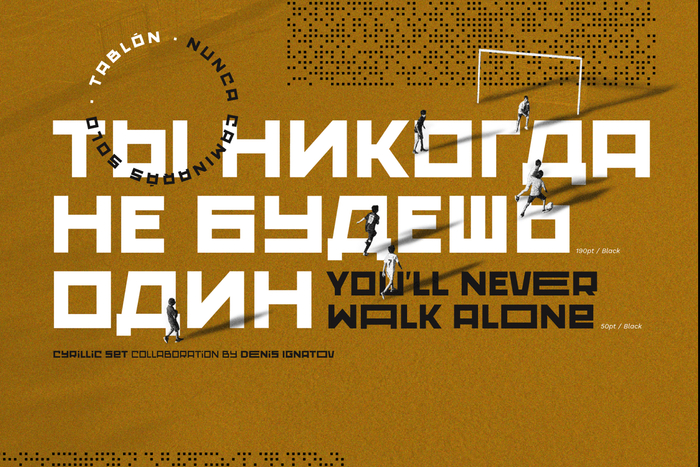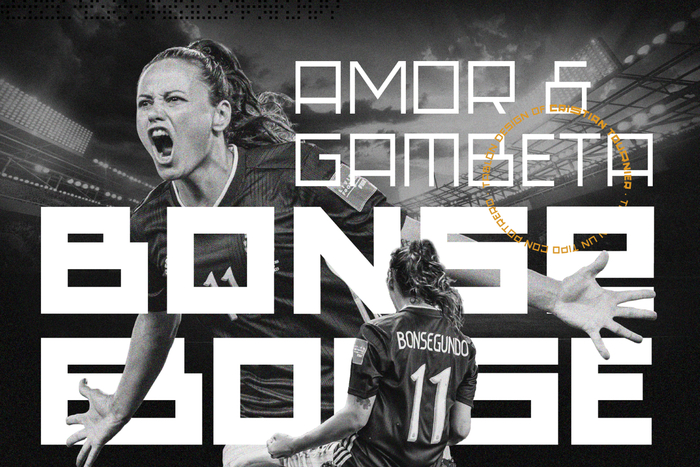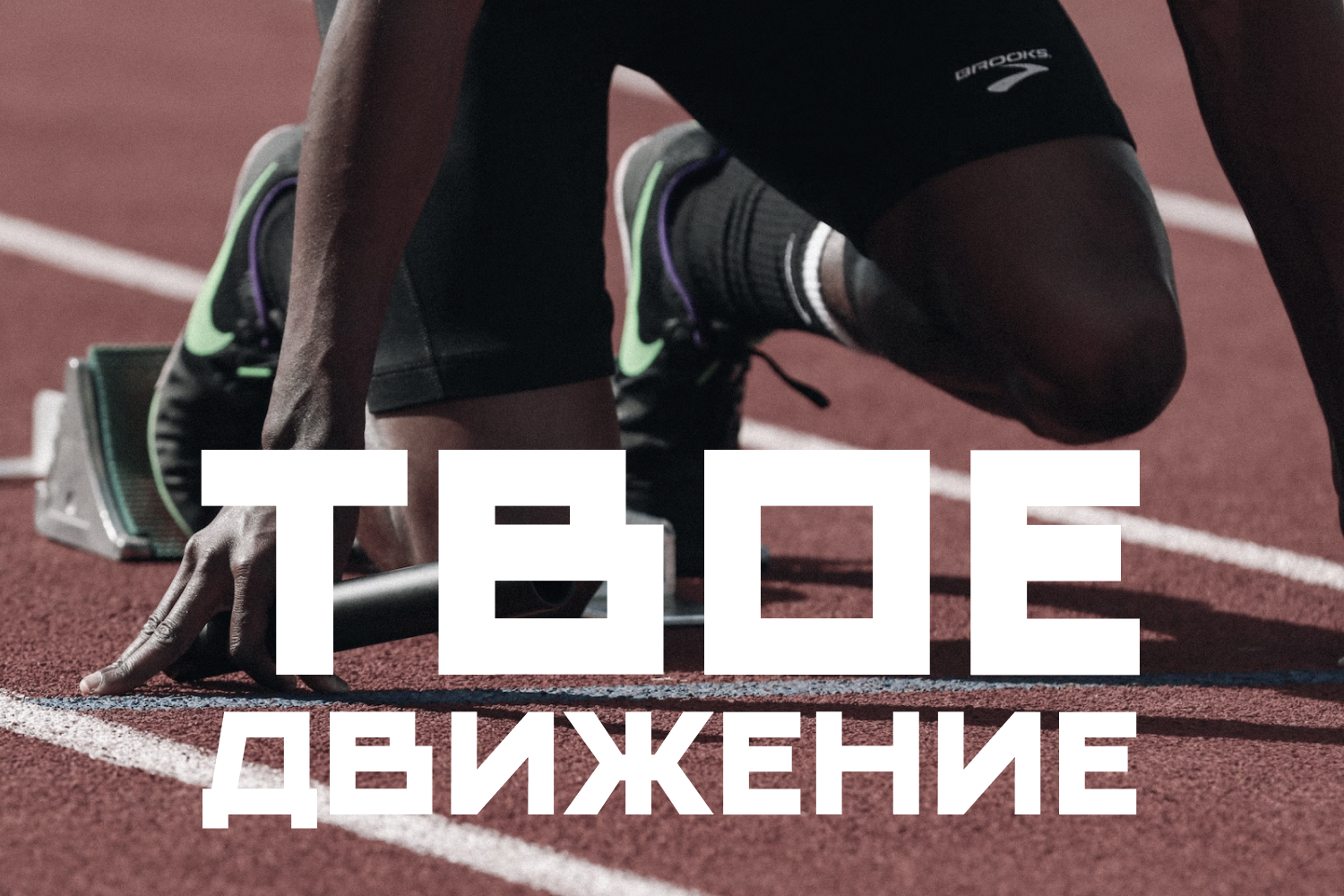
Шрифт Tablon. Кириллица
Привет пикабу! Спортивный шрифт Таблон Таблонович зовет тебя на зарядку. Пора размять свои затверденелые булки. Прям сейчас сделай 3 приседания или отжимания.
Автор: Cristian Tournier